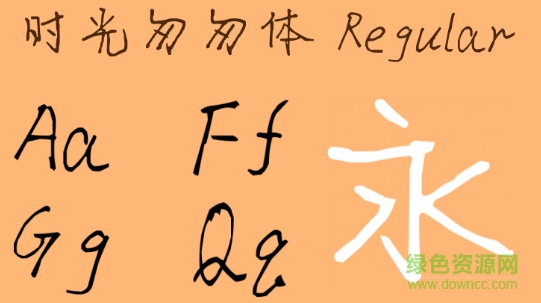
時光匆匆體字體
OPPO字體時光匆匆體ttf版是一款漂亮的手寫字體,字體骨骼清秀,筆畫錯落有致,簡潔優(yōu)雅,廣告設(shè)計或網(wǎng)頁設(shè)計都用得到,喜歡這款字體的朋友快來綠色資源網(wǎng)下載吧!
手寫體特點
大大小小,風(fēng)格不一,帶著體溫的書寫出來的字體。
手寫體制作步驟
手寫體文字是用“美工筆”在紙上寫出來的,可能一個字會寫幾十遍或者更多,之后再從中間選出寫的比較可以接受的拍照,上傳到電腦上用photoshop處理后制作而成。